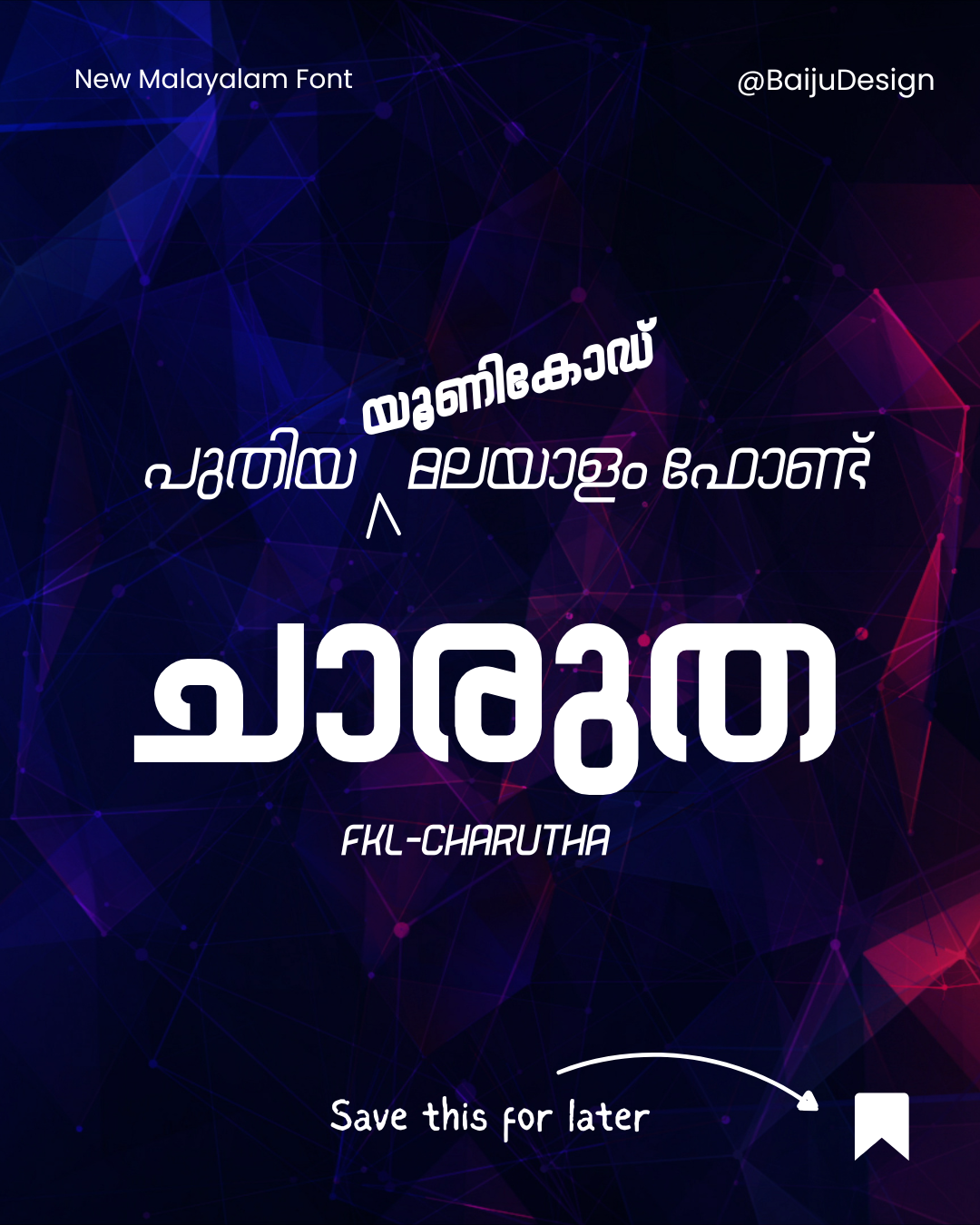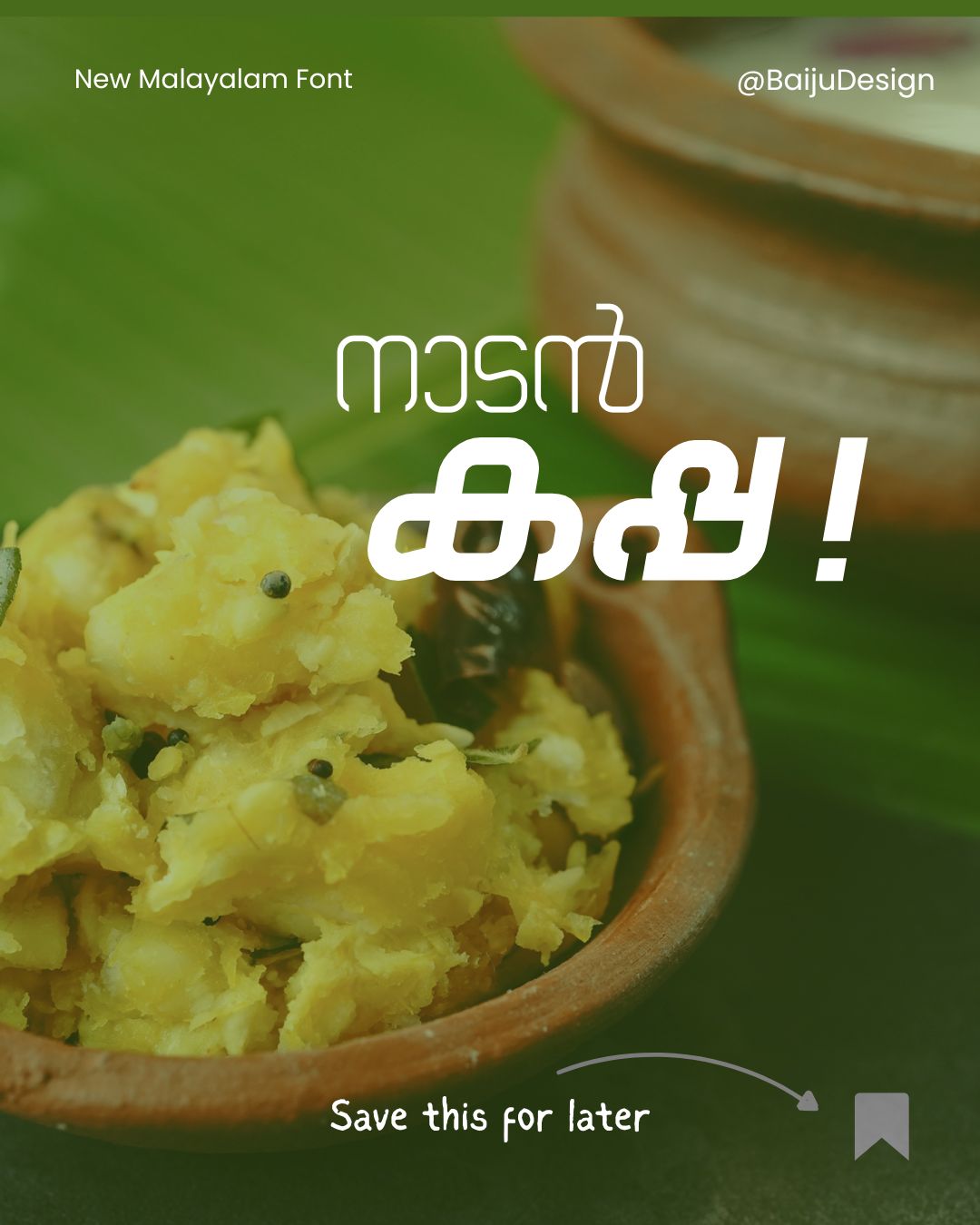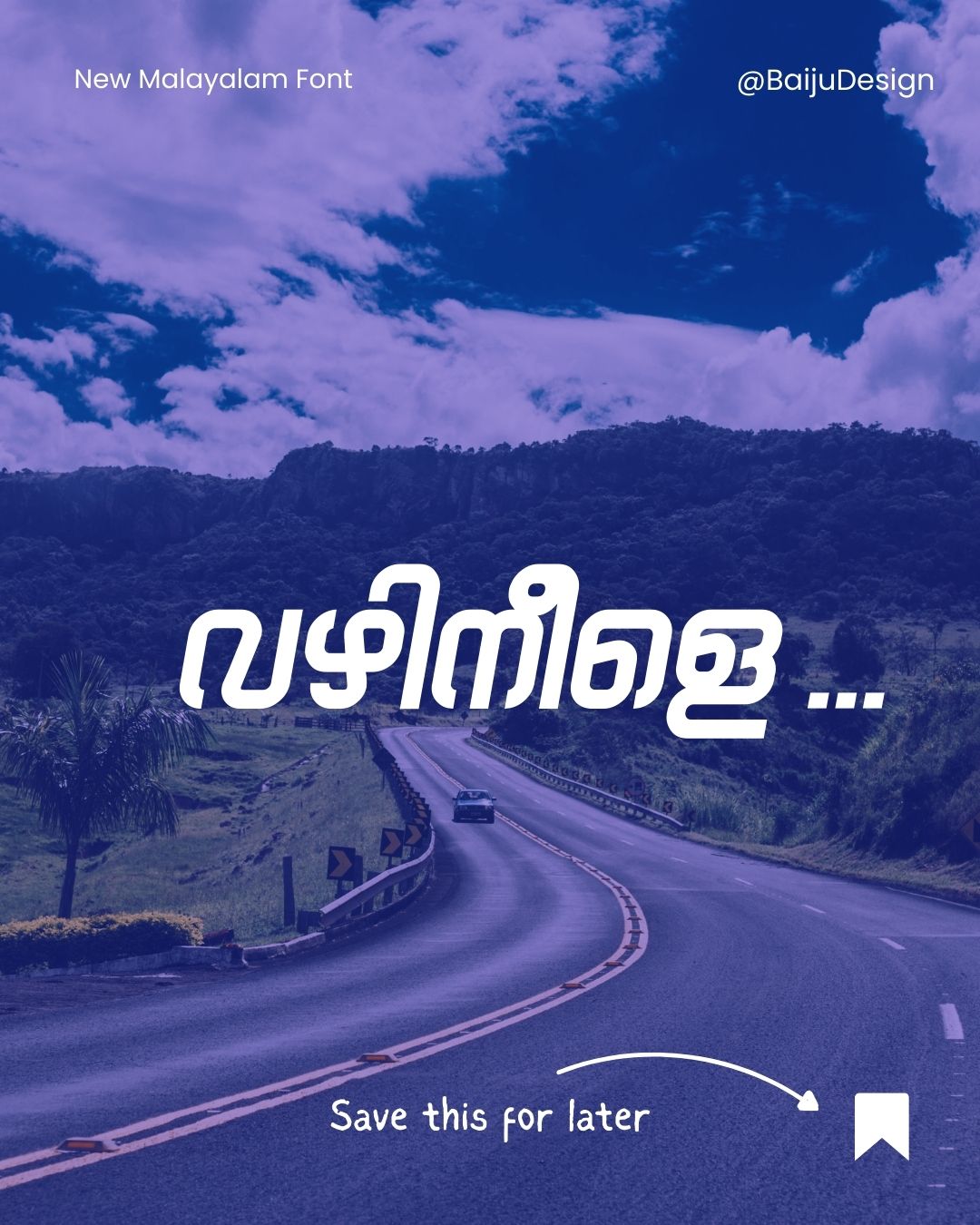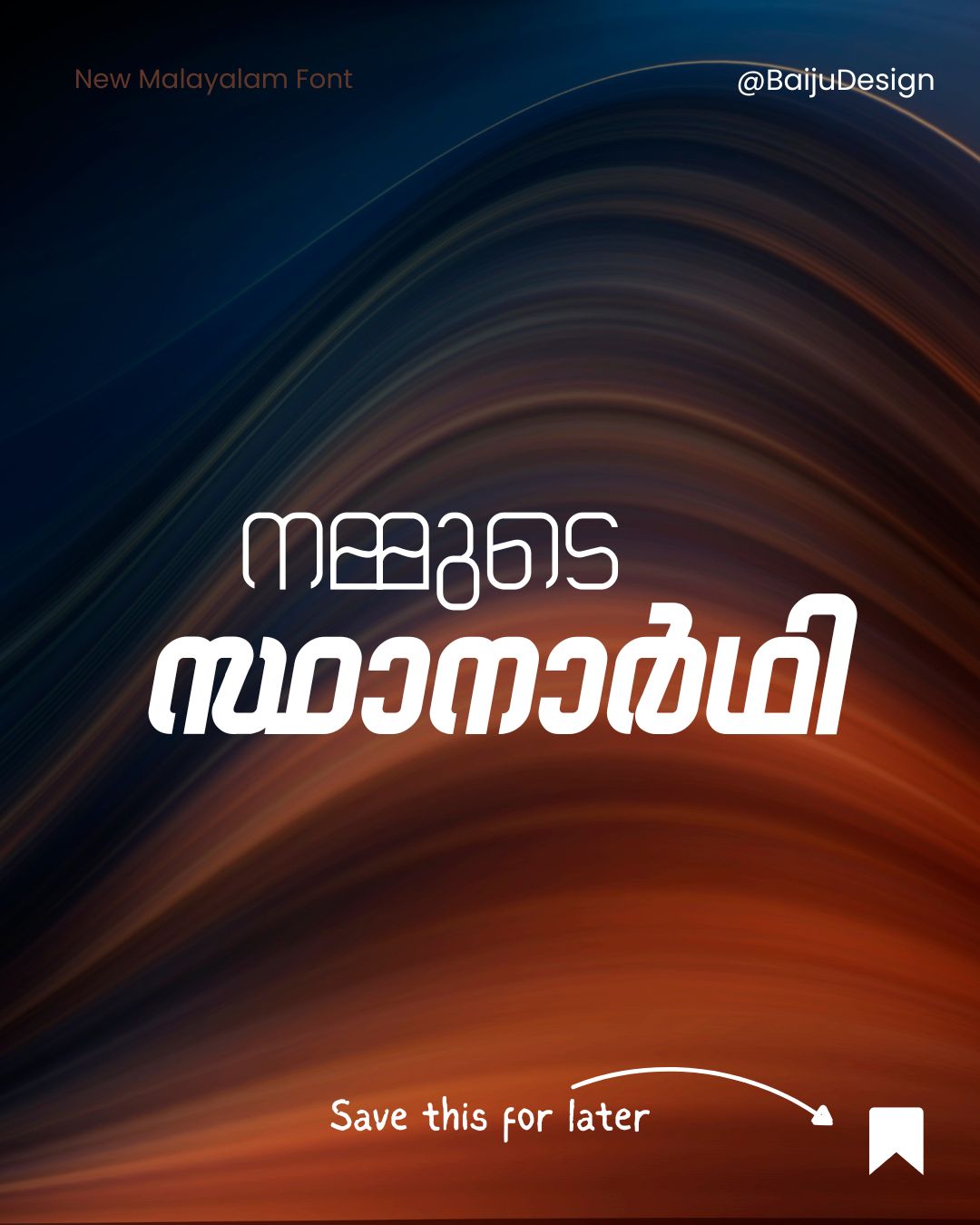
New Malayalam Font FN Charutha Unicode
✨ മലയാളത്തിലെ ഏറ്റവും പുതിയ സാൻസ് സെരിഫ് യുണീക്കോഡ് ഫോണ്ട്.
✨ ഒരു പാക്കേജിൽ 16 വ്യത്യസ്ത വേരിയേഷൻസുകൾ.
✨ പരിഷ്കരിച്ച മലയാളം ലിപി ആയതിനാൽ കൂടുതൽ ഗ്ലിഫുകൾ, കൂട്ടക്ഷരങ്ങൾ.
✨ പോസ്റ്ററുകൾ, ഹോർഡിംഗുകൾ, പത്ര പരസ്യങ്ങൾ എന്നിവയ്ക്ക് ഉപയോഗിക്കാൻ കഴിയുന്ന മനോഹരമായ ഫോണ്ട്.
✨ വലിയ ഹോർഡിങ്, പോസ്റ്റർ എന്നിവക്ക് അനുയോജ്യം.
✨ തിരഞ്ഞെടുപ്പ് പോസ്റ്ററുകൾ, ന്യൂസ് കാർഡുകൾ, വീഡിയോ തമ്പ്നെയിലുകൾ എന്നിവയ്ക്ക് വേറിട്ട ദൃശ്യചാരുത സമ്മാനിക്കും.
Font NameFN Charutha
Font TypeDisplay & Title
Creator / DesignerFont Ashan